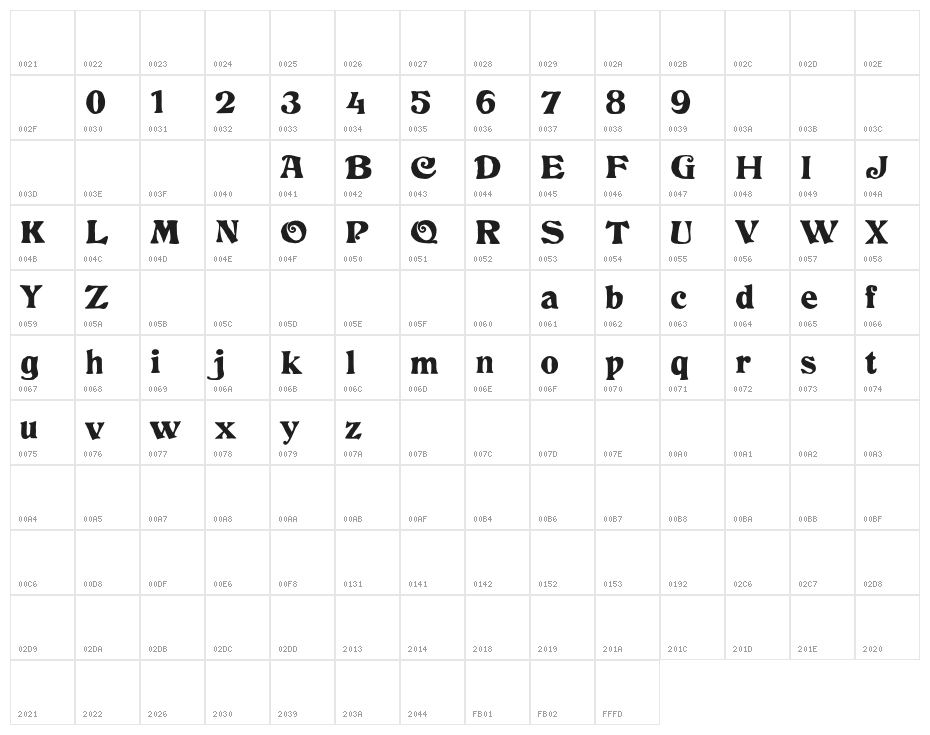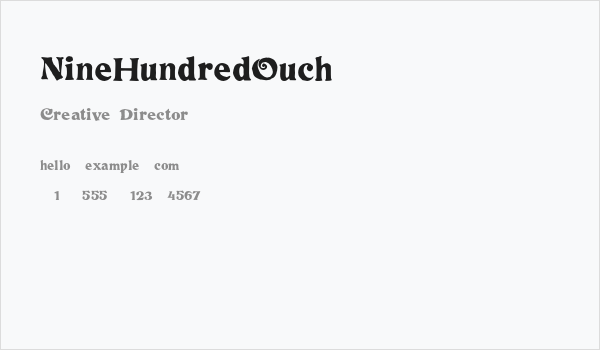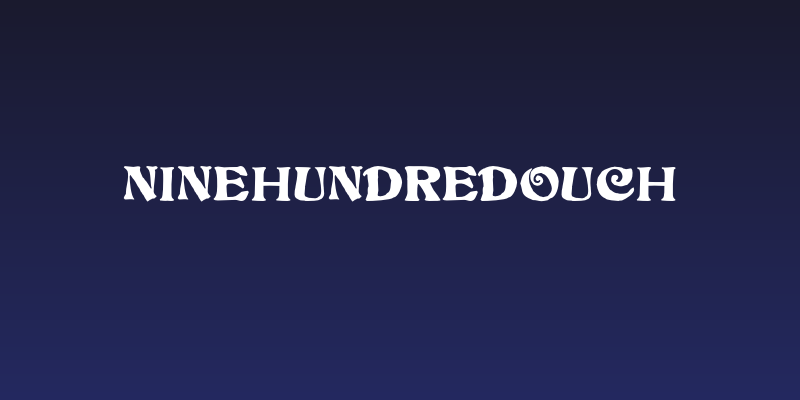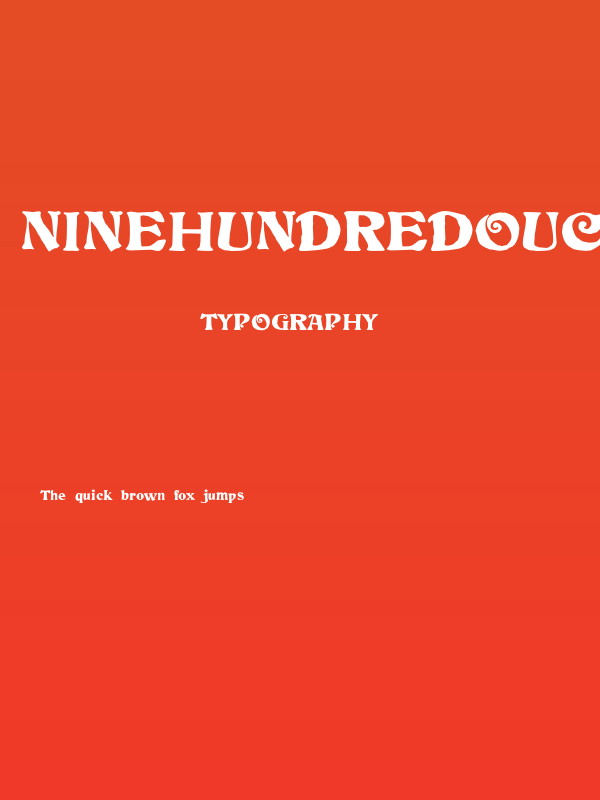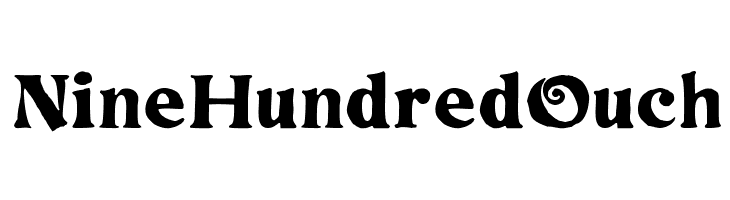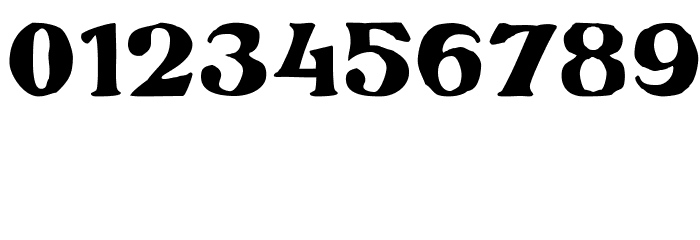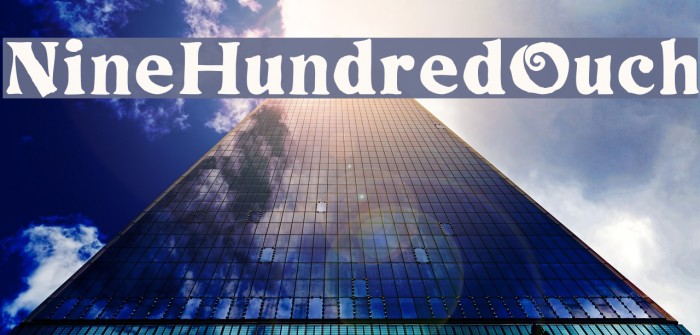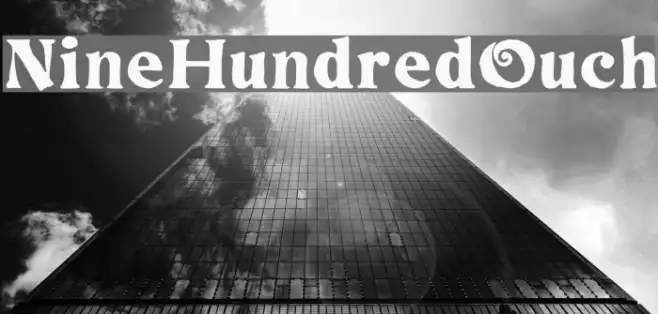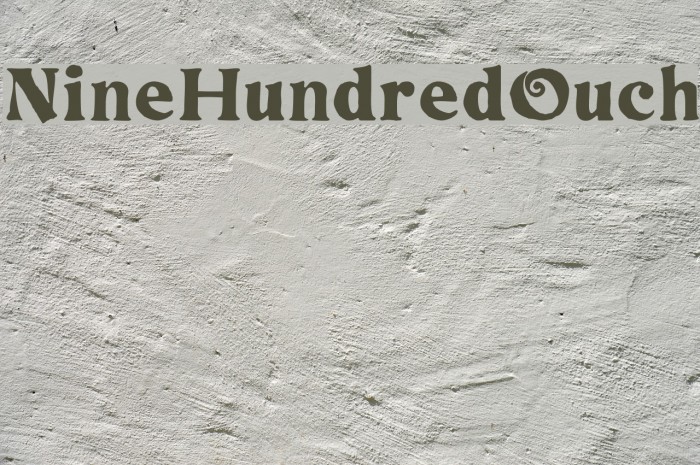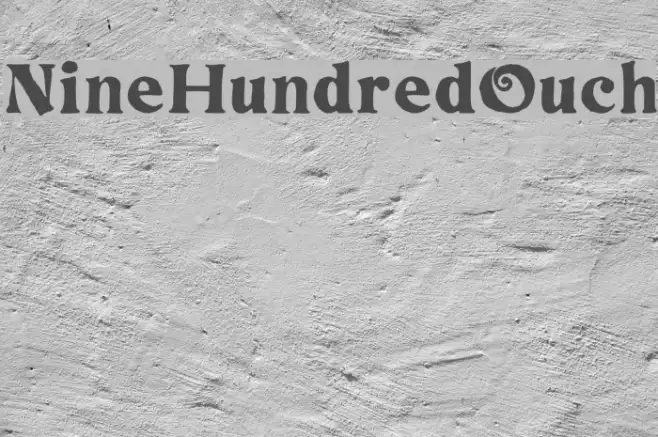
NineHundredOuch Font
| Stile generale | Playful, Whimsical |
| Progetti proposti | Ideal for children's books, playful branding, party invitations, and creative posters. |